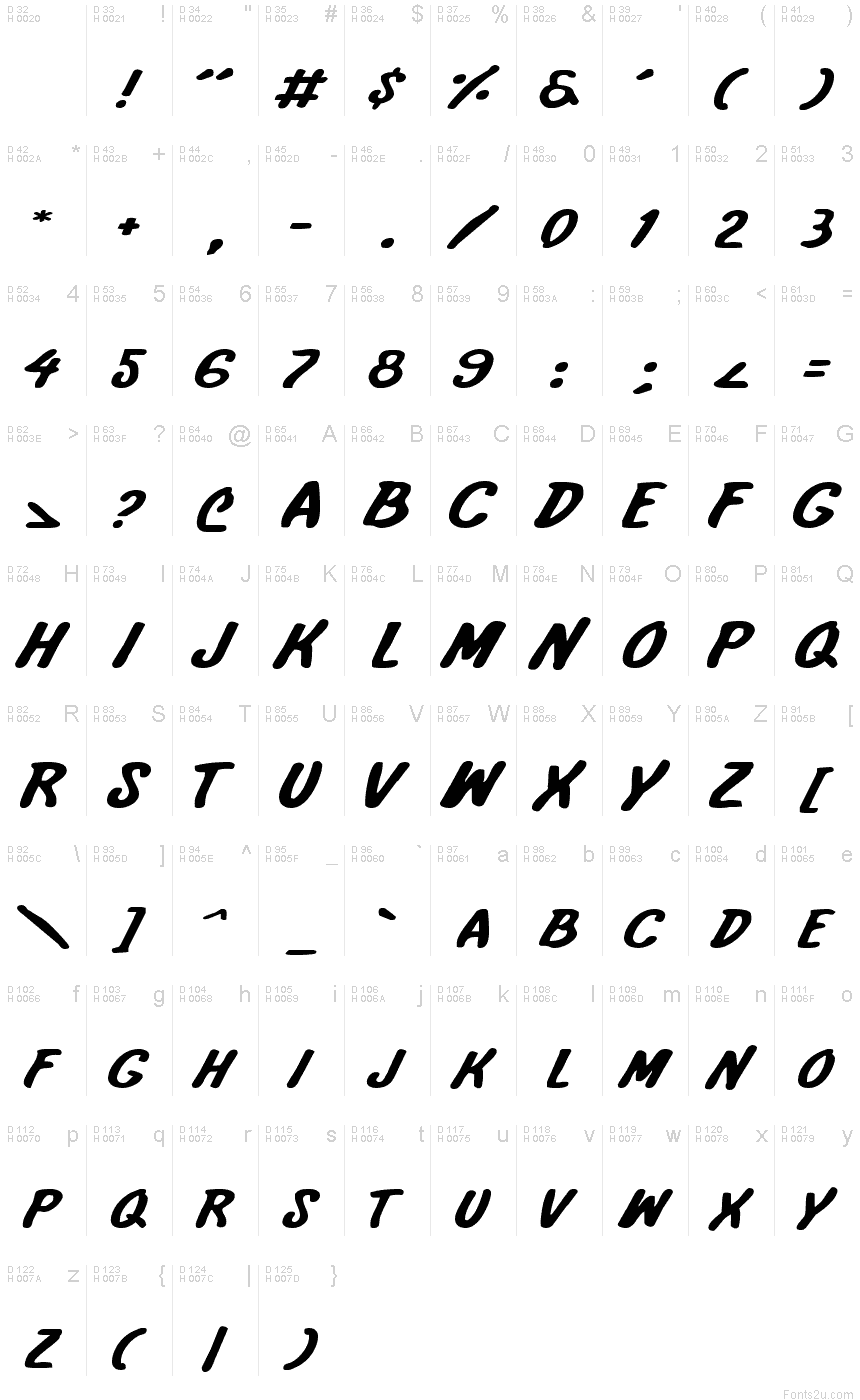
Il font International Super Hero Exp di Iconian Fonts è un carattere tipografico gratuito in stile fumetto che colpisce con l'impatto di un pannello d'azione disegnato a mano. Le lettere si inclinano in avanti con un movimento rapido e fluido, e i tratti spessi e carichi di inchiostro sembrano pennellate dirette sulla pagina. Ha un aspetto forte ed energico, capace di dare dinamismo ai titoli anche quando sono fermi.
Con International Super Hero Exp, potrai creare copertine di fumetti, loghi di supereroi, poster per bambini, titoli di giochi, confezioni di giocattoli e miniature di YouTube di grande impatto. Questo font gratuito dà il meglio di sé in grande formato e in primo piano, dove le sue curve dinamiche e irregolari possono davvero urlare; abbinalo a un carattere sans serif semplice e neutro per didascalie o testi secondari per mantenere i tuoi layout leggibili e focalizzati.